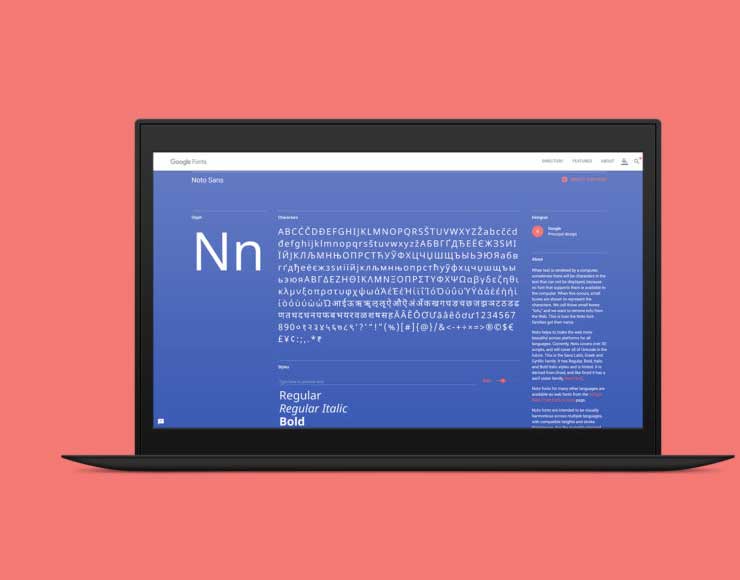
Per consentire agli utenti di semplificare la creazione e la condivisione di informazioni nella lingua preferita, Google ha creato Noto, una famiglia di font open source che tiene conto di oltre 8000 lingue e supporta 110.000 caratteri. La famiglia di caratteri copre in pratica ogni singolo simbolo riconosciuto dallo standard Unicode.
Il progetto, nato per rendere Android e ChromeOS più accessibili, ha richiesto cinque anni per il completamento e ha visto il coinvolgimento di esperti del mondo tipografico di Monotype e Adobe.
Il nome Noto, spiega TheNextWeb, nasce dalla frase ‘No more tofu’, riferimento alo sbarazzarsi nel web di quei caratteri visualizzati quando il simbolo necessario per una certa lingua non è disponibile nel sistema dell’utente. Sfruttando Noto è possibile visualizzare liberamente i simboli di qualsiasi lingua.
Google ha anche aggiornato i suoi web font (caratteri che è possibile sfruttare fruttando la direttiva CSS @font-face per far scaricare e consentire all’utente di usare qualunque carattere tipografico). Il progetto Noto è open source e dal repository GitHub è possibile scaricare anche i file sorgenti usati nella fase di design. Google afferma che continuerà ad aggiornare Noto integrando il supporto a nuove lingue e caratteri Unicode.